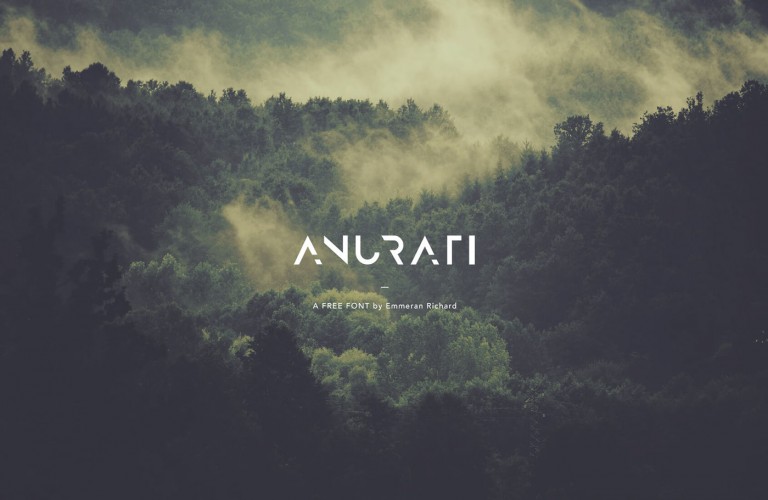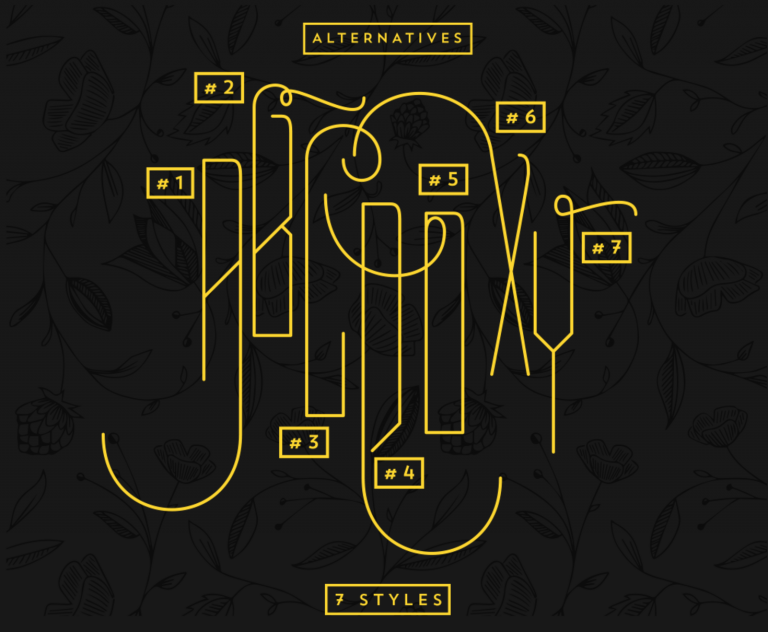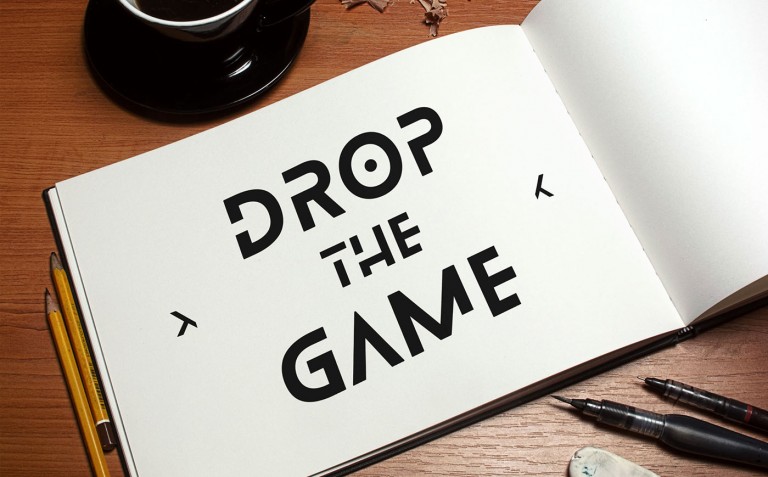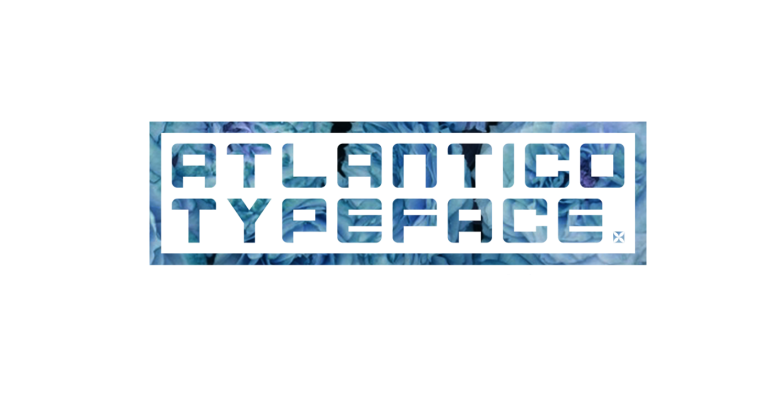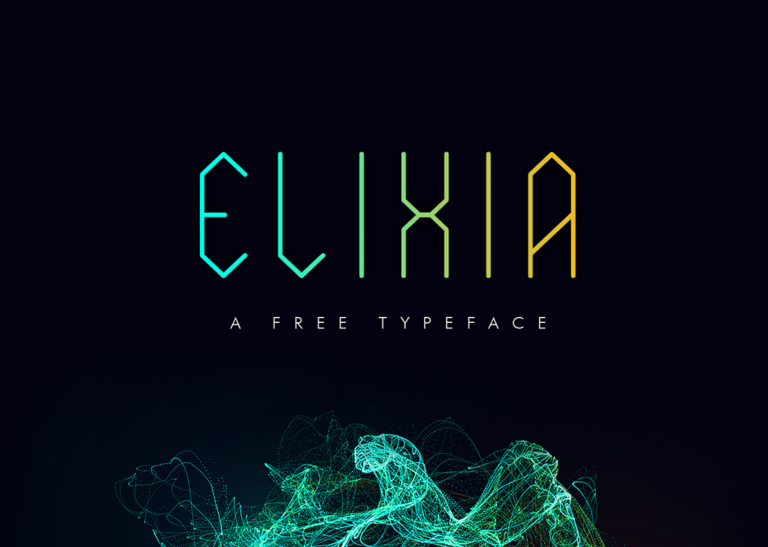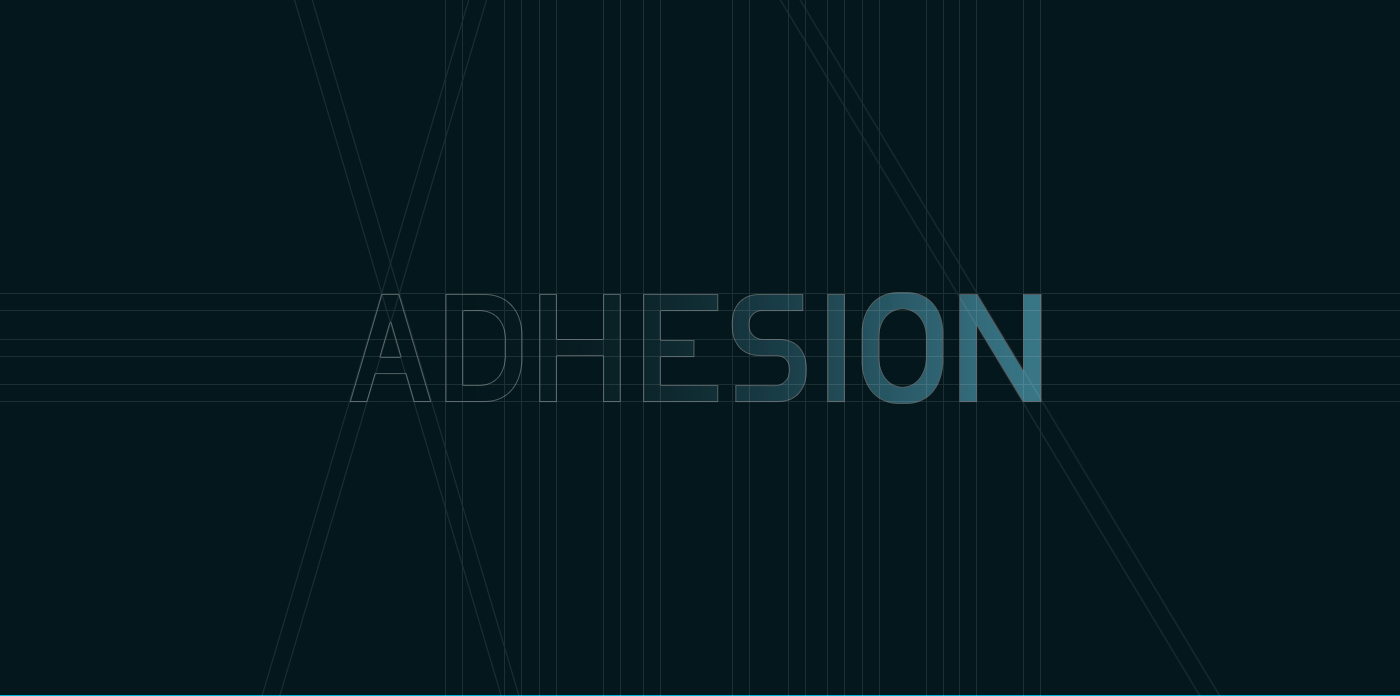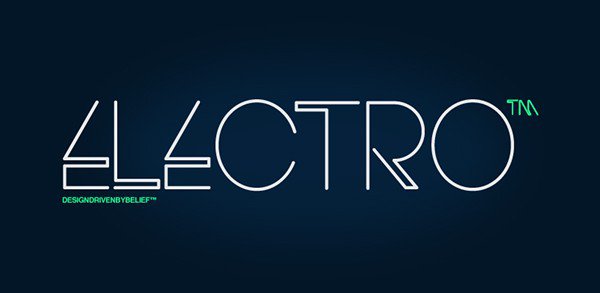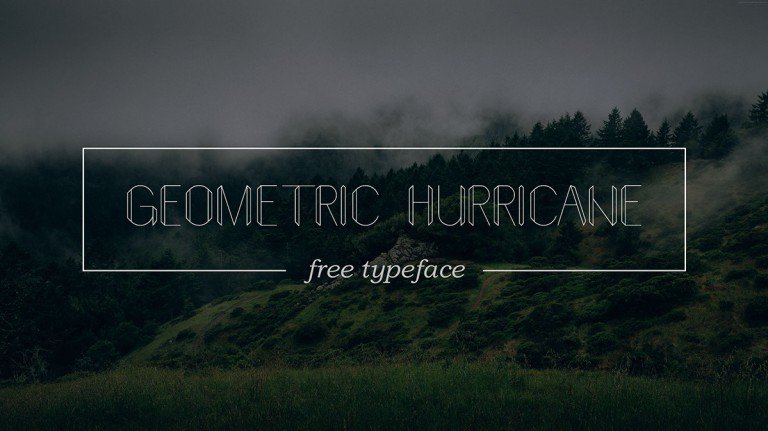
Lựa chọn được một kiểu chữ mang cảm giác về tương lai (futuristic) cho thiết kế của bạn sẽ mang lại thật nhiều cảm xúc.
Bởi thiết kế hiện đại luôn tạo đà cho trí tưởng tượng của nhà thiết kế, để ta tự hỏi chính mình dám phá bỏ các ranh giới. Kiểu chữ futuristic luôn luôn phá vỡ các khuôn mẫu theo những cách đẹp nhất.
Nếu bạn vẫn đang săn tìm một futuristic font yêu thích, hãy kéo xuống dưới đây. Chúng mình đã tìm thấy 50 fonts chữ futuristic tuyệt vời và hoàn toàn miễn phí cho bạn sử dụng ngay vào thiết kế của mình. Nhiều fonts trong số này đẹp nhất khi đặt ở kích thước lớn, nhưng dưới đây cũng có sẵn một số font linh hoạt hơn và bonus thêm mình một số phần khác của một thiết kế như tiêu đề hoặc quotes.
Hãy cùng RGB làm quen với 50 phông chữ futuristic dưới đây nha.
01. Anurati
Xuất hiện đầu tiên trên danh sách của chúng tôi là Anurati, một kiểu chữ futuristic đáng yêu của Emmeran Richard, dựa trên những quy tắc của sự khép kín tạo nên cái nhìn thú vị cho form chữ của nó. Đặt Anurati font lên hình ảnh hay một khối màu, sự kết hợp đó sẽ ngay lập tức mang lại cho bạn một “cảm giác tương lai”.
02. Luciana
Luciana là một font chữ đơn hiện đại, đáng yêu và hơi khác biệt. Nó bao gồm các cặp nét Ultra light cùng với một bộ các nét cong lượn sóng hoàn hảo, tạo nên một cảm giác nữ tính và năng động.
Các kiểu chữ đều có thể tải về miễn phí và hoàn toàn có thể chỉnh sửa. Sử dụng nó trên poster hoặc để dùng nó cho logo của bạn là quá tuyệt rồi.
03. Blanka
Blanka, cũng được thiết kế bởi Emmeran Richard, là một kiểu chữ tối giản. Được thiết kế để tạo nên cảm giác như nó đến từ một khoảng thời gian nào đó ở phía trước. Bạn hẳn sẽ yêu các các nét bị khuyết từ form chữ của nó, là cách họ làm cho font chữ này mang cảm giác vui tươi. Sử dụng cho một tiêu đề lớn? Blanka chính là một lựa chọn tuyệt vời.
04. Atlantico
Lấy cảm hứng từ Đại Tây Dương (Atlantic) rộng lớn, Atlantico là một bộ sans-serif hình học của phông chữ tạo cảm giác như nó sinh ra là để dành cho poster nhạc dance điện tử. Đó là kiểu chữ dày và đậm, kết thúc bằng cả đường cong tròn và vuông. Thiết kế cho một lễ hội âm nhạc khiêu vũ hay EP? Hãy luôn ghi nhớ Atlantico trong tâm trí.
05. Elixia
Elixia, một typeface được xây dựng từ hình lục giác. Nó không chỉ giúp bạn tạo cảm giác tương lai, nó cũng giúp tạo nên sự thần bí, cảm giác cổ xưa. Hãy sử dụng nó như là một phông chữ trang trí. Như ví dụ phía trên đây.
06. Nidus Sans
Nidus Sans là một phông chữ sans-serif. Nó không chỉ hoạt động tốt như một display font mà còn có thể sử dụng trong các phần nhỏ của thân bài viết. Nếu bạn không quan tâm lắm đến một kiểu chữ quá biểu cảm, hãy cho Nidus Sans một vote nhé.
07. Electro
Nói về kiểu chữ biểu cảm, Electro là một sự kết hợp tuyệt đẹp của các cạnh sắc nét và các đường line mỏng. Electro cung cấp một phiên bản miễn phí với một vài hạn chế (không hỗ trợ ngôn ngữ hoặc dấu chấm câu). Phiên bản dùng thử cho phép bạn sử dụng kiểu chữ này trong bất cứ thiết kế bạn muốn mà không cần phải bỏ ra một đồng nào.
[quote] 08. Ultra[/quote]
Ultra, như bạn có thể nói từ hình ảnh anh hùng của nó, được lấy cảm hứng từ ánh đèn neon. Fabien Korn gợi ý rằng bạn có thể ứng dụng nó trong nhiều màu sắc. Tôi đã từng thử với màu xanh lime và hot pink – hey, màu neon mang lại cảm giác cực kì điên rồ.
[quote] 09. Geometric Hurricane[/quote]
Thử ngay Geometric Hurricane, một lựa chọn tuyệt vời khác cho display font.
[quote] 10. Raptor Sans[/quote]
Raptor Sans thực sự tạo ra cảm giác retro, khi nghiên cứu về nó bạn sẽ cảm thấy như vậy. Nó là 1 font chữ đậm (bold), đơn giản và dễ hiểu. Nếu bạn muốn thêm một cảm giác retro cho bất kỳ cảm giác futuristic nào trong thiết kế của mình, hãy nhớ đến Raptor Sans.
Các nhà thiết kế Raptor Sans, Panos Voulgaris, đã tạo nên một bìa sách từ những năm 60 và 70 để nói lên sự tuyệt vời mà Raptor Sans mang lại. Hãy tham khảo chúng trên Behance.
[quote] 11. Lazerz Additktz[/quote]
Bạn muốn biết được vẻ rực rỡ của Lazerz Additkz? Hãy xem tác phẩm trên Behance. Ở đó, bạn sẽ tìm thấy được tất cả sự huy hoàng của nó được giới thiệu thông qua một loạt các chuỗi hình gifs và những cách xử lý cực ngầu có thể tạo cho bạn một cảm giác muốn sử dụng ngay font chữ đó.
[quote] 11. Fuerte[/quote]
Fuerte, cũng giống như Nidus Sans, đem đến một cảm giác tương lai tinh tế hơn. Nhà thiết kế Manh Nguyen – người thiết kế cả letterforms và pattern đã chuẩn bị để bạn bắt tay vào cuộc hành trình thiết kế futuristic của bạn.
[quote] 13. Ailerons[/quote]
Ailerons là một kiểu chữ cân đối, dễ đọc và phong cách với letterforms cao đẹp và có thể nhanh chóng cách điệu hóa bất kỳ tiêu đề nào. Đặt chữ tiêu đề của bạn ở một kích thước lớn và chiêm ngưỡng tất cả các chi tiết đáng yêu tạo nên mỗi nét chữ.
Nhấn vào đây để tải về: ailerons.
[quote] 14. Beyno[/quote]
Cần một kiểu chữ cho poster? Hãy thử Beyno. Letterforms kỳ quặc và khác biệt của nó có thể cách điệu hóa bất kỳ phần nội dung nào. Một số các nét chữ trong bộ này, ví dụ như chữ “n” thực sự rất thú vị.
Nhấn vào đây để tải về: Beyno.
[quote] 15. Borg[/quote]
Mỗi nét chữ trong Borg với các đường cong sắc bén đã tô điểm thêm sự chuyển động cho letterforms này. Mỗi con chữ đều rút ngắn một cách gon gàng, xinh đẹp và siêu dễ đọc. Có thể sử dụng Borg trên t-shirt, như một kiểu chữ hiển thị, hoặc thậm chí để thiết kế một logo ngọt ngào.
Nhấn vào đây để tải về: Borg.
[quote] 16. Elianto[/quote]
Elianto, với chữ A tam giác đáng yêu, là một phông chữ sans-serif miễn phí có sẵn cho người dùng cá nhân. Nó đi kèm trong cả chữ thường, chữ viết hoa và có một vài cách điệu xen kẽ cho nhiều nét chữ.
Nhấn vào đây để tải về: Elianto.
[quote] 17. Exan-3[/quote]
Thoả mãn cơn thèm muốn futuristic của bạn với Exan-3, một phông chữ tương lai đơn cách (monospace) với một cảm giác retro. Sử dụng nó trên các poster, bussiness card hoặc bất kỳ tài liệu nào khác để thể hiện hết được phong cách của tương lai.
Nhấn vào đây để tải về: Exan-3.
[quote] 18. Azedo[/quote]
Azedo là một font “thấp” với các chi tiết siêu thú vị trên các nét chữ của nó. Tôi hoàn toàn yêu thích chữ cái A viết hoa và thanh cùng các nét cong tròn của nó. Font chữ nhiều chi tiết thanh lịch này là một sự lựa chọn tuyệt vời cho một tiêu đề hoặc một logo đẹp.
Nhấn vào đây để tải về: Azedo.
[quote] 19. Stellar[/quote]
Điều tôi thích ở Stellar là tính linh hoạt của nó. Với cách sử dụng đúng, ta hoàn toàn có thể cảm thấy như font chữ này nằm trên bề mặt của một tàu thăm dò không gian quay quanh sao Thổ.
Nhấn vào đây để tải về: Stellar.
20. Neptune
Góc độ điên rồ và nét chữ sôi nổi là những phần nổi bật của Neptune, một kiểu chữ hiện đại mang nhiều ý nghĩa chắc chắn sẽ gây sự chú ý của bất kỳ ai. Nó hoàn hảo cho các poster, logo, hoặc đóng vai một kiểu chữ chính trên một thiết kế hiện đại.
Nhấn vào đây để tải về: Neptune.
21. UFO Nest
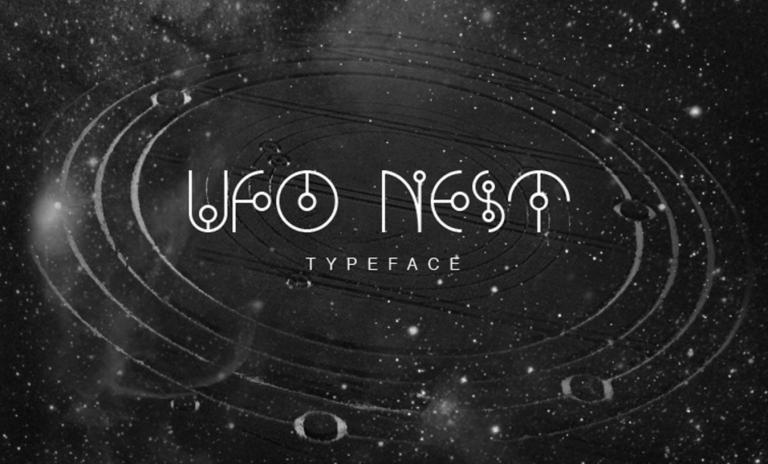
Như bạn có thể tưởng tượng, UFO Nest đã được truyền cảm hứng bởi các “crop circle” và sự bí ẩn xung quanh nó. Đây là một kiểu chữ khá phức tạp, nên sử dụng nó cho các tiêu đề hoặc nội dung bạn sẽ đặt ở kích cỡ lớn. Với body copy dùng ở font chữ UFO Nest sẽ hơi khó đọc.
Nhấn vào đây để tải về: UFO Nest.
22. Arkhip
Arkhip có điểm đặc biệt với những đường cong lượn sóng làm thêm chuyển động và cái nhìn thú vị cho con chữ. Tôi yêu sự hợp lý của nó khi hiển thị ở nhiều kích cỡ và vẫn đọc tốt, không giống như nhiều kiểu chữ khác trong list font chữ này.
Nhấn vào đây để tải về: Arkhip.
23. Dual
Dual đi kèm với hơn 250 phong cách xen kẽ, làm cho những thứ bạn có thể tạo ra từ nó trở nên bất tận. Xem các project trên Behance và cùng nhìn các nét chữ khác nhau hoàn toàn có thể thay đổi cái nhìn của kiểu chữ như thế nào. Bạn cũng nên chú ý vào ký tự “&” của nó – font chữ này thực sự tuyệt đẹp!
Nhấn vào đây để tải về: Dual.
24. Astro
Astro là một typeface lấy cảm hứng từ thiên văn học. Mặc dù chúng tôi giới thiệu về font chữ này ở dạng chữ viết hoa toàn bộ (all caps), nhưng hãy thử viết nó ở dạng chữ thường. Trông nó thật đẹp!
Nhấn vào đây để tải về: Astro.
25. Halogen
Tìm kiếm một cái gì đó thật đậm và mạnh mẽ? Hãy thử Halogen. Nó cũng giống như nhiều của các kiểu chữ khác, kiểu chữ này có sự cách điệu xen kẽ . Đây là một font chữ tuyệt vời khi ai đó yêu cầu bạn tạo ra một logo từ tốt đến tuyệt vời.
Nhấn vào đây để tải về: Halogen.
26. Marske
Marske là một kiểu chữ hiển thị all caps lấy cảm hứng từ giấy nến. Nó có những phần khác nhau phù hợp với nhau như một liên kết, tạo cho letterforms một cảm giác mạnh mẽ và táo bạo.
Nhấn vào đây để tải về: Marske.
27. Phage
Tìm kiếm một cái gì đó khó quên? Hãy tìm đến Phage!
Nhấn vào đây để tải về: Phage.
28. Savone
Savone cung cấp các góc độ đậm nhưng biểu cảm hơn những typeface trong danh sách này.
29. Chronic
Chronic được lấy cảm hứng từ huyền thoại Native America và hình học. Nét chữ rối của nó sẽ không phù hợp với đoạn body copy nhưng sẽ hiển thị một cách đẹp nhất ở kích thước lớn trong tiêu đề.
Nhấn vào đây để tải về: Chronic
30. Good Times
Good Times được lấy ý tưởng từ những ký tự sử dụng trên những chiếc xe Pontiac từ những năm 80. Hãy sử dụng font chữ này để mang lại nguồn cảm hứng cổ điển cho các tiêu đề hoặc để tạo một dấu ấn sâu sắc.
Nhấn vào đây để tải về: Good Times
31. Moki Mono
Moki có 7 kiểu dáng khác nhau. Hãy thử kết nối chúng theo những cách khác biệt hoặc dùng chúng trên các poster.
Nhấn vào đây để tải về: Moki Mono.
32. Nasalization
Bạn có nhớ logo của Nasa năm 1975? Nasalization được thiết kế với 6 mức độ đậm nhạt khác nhau cho bạn tùy ý lựa chọn. Bạn muốn thiết kế một chủ đề về du hành vũ trụ? Hãy thử Nasalization!
Nhấn vào đây để tải về: Nasalization.
33. FM Pointiflax
Với cách sử dụng đúng đắn, kiểu chữ này như đến từ thế giới công nghệ trong quá khứ, mang lại cảm giác hoài cổ.
Nhấn vào đây để tải về: FM Pointiflax
34. Oboe
Bạn đang tìm kiếm một loại ký tự chữ đậm và mập mạp? Oboe chính là thứ bạn cần. Với đường nét cứng cáp, bầu bĩnh, thật khó để không bị ấn tượng và thật tuyệt khi dùng Oboe để định vị chất riêng cho nội dung bài của bạn.
Nhấn vào đây để tải về: Oboe.
35. Celari Titling
Bạn muốn tạo ra sự chuyển động? Hãy sử dụng font chữ đầy cá tính Celari Titling. Những đường đứt đoạn trên các con chữ khiến bộ chữ của bạn trông thật bùng nổ và sống động.
Nhấn vào đây để tải về: Celari Titling
36. Outage
Outage là loại font chữ đứng có thể dùng cho hai phong cách khác nhau. Hãy thử nó trên áo phông, để thể hiện cá tính, hoặc dùng cho các logo.
Nhấn vào đây để tải về: Outage
37. Finity
Finity là loại font chữ mang hơi hướng tương lai, phức tạp và rất bắt mắt, sẽ thu hút sự chú ý khi dùng cho bất kỳ bài viết nào. Hãy cẩn thận đừng để chữ quá nhỏ khi dùng font này vì sẽ rất khó đọc.
Nhấn vào đây để tải về: Finity
38. Lambok
Lambok, cũng giống như những loại font chữ phần đầu danh sách, mang lại cảm hứng thú vị khi nhìn. Chữ “b” trông hơi giống miếng gót giầy hoặc các dữ liệu hay mảnh ghép ký tự.
Nhấn vào đây để tải về: Lambok
39. Baron
– Quảng cáo –
Baron là một kiểu chữ khác mà bạn có thể sử dụng theo nhiều cách khác nhau để diễn đạt những cảm xúc khác biệt. Hãy thử dùng các chữ ghép hay ký tự dùng để làm cho các từ ngữ có thêm hiệu ứng chuyển động. Chúng vô cùng thú vị.
Nhấn vào đây để tải về: Baron.
40. Sacred Geometry
Sacred Geometry là một kiểu chữ vô cùng phức tạp mà bạn sẽ phải sử dụng ở cỡ vô cùng lớn. Hãy dùng trên poster hay chỉ dùng một chữ một lần cỡ lớn như một yếu tố trang trí.
Nhấn vào đây để tải về: Sacred Geometry
41. Mylodon
Mylodon có 2 kiểu: Light và Regular . Thông thường, nó được dùng làm font chữ hiển thị, nhưng vẫn có thể dùng ở kích thước nhỏ hoặc số lượng ít trong body copy.
Nhấn vào đây để tải về: Mylodon.
42. Beams
Beams đưa ra một sự kết hợp giữa góc cạnh và góc tròn làm cho thiết kế tạo thành hình rõ rệt. Đó là sự kết hợp táo bạo, bắt mắt và chắc chắn sẽ tạo nên điều gì đó mà khán giả của bạn không thể rời mắt được.
Nhấn vào đây để tải về: Beams
43. Wormbox
Wormbox là một kiểu font giống như tiêu đề của một video game. Nếu bạn đang thiết kế những thứ giống như vậy, hãy sử dụng Wormbox.
Nhấn vào đây để tải về: Wormbox
44. Strato
Strato là một bảng chữ cái nội tuyến hình học giống như được làm bằng đèn led. Gây ra cảm xúc mạnh, vì vậy hãy sử dụng để khiến mọi người nhận ra nó ngay lập tức.
Nhấn vào đây để tải về: Strato
45. VGER
Bạn thích cái poster phía trên chứ? Nó được thiết kế bằng việc sử dụng VGER, một trong những kiểu chữ yêu thích của tôi trong danh sách này. VGER có những độ dày đâm của font chữ khác nhau, cho phép bạn dễ dàng xây dựng các cấp bậc khác biệt với chỉ cùng một kiểu chữ.
Nhấn vào đây để tải về: VGER
46. Digital
Chọn Digital và làm một câu quote với nó. Chèn vào một poster hoặc T-shirt và chia sẻ với cả thế giới ngay thôi.
Nhấn vào đây để tải về: Digital
47. Yukarimobile
Tôi ưa Yukarimobile và kiểu chữ hình học đậm, in nghiêng của nó. Các font chữ đi kèm theo với một vài mảnh ghép tuyệt vời cho những chi tiết ngọt ngào trong một logo.
Nhấn vào đây để tải về: Yukarimobile
48. Dylovastuff
Ban đang muốn làm một câu quote về không gian? Hãy thử với Dylovastuff. Letterforms tròn và cut-out của nó sẽ làm cho poster của bạn đẹp lên.
49. Three-Sixty Condensed
36 Condensed là letterforms hợp lý nhất để có thể thêm dấu ấn cá nhân.
50. Neogray
Và cuối cùng, chào mừng Neogrey. Form chữ viết của người ngoài hành tinh cổ điển khiến nó trở thành một font chữ không thể thiếu trong bất cứ bộ sưu tập các font chữ của tương lai nào.